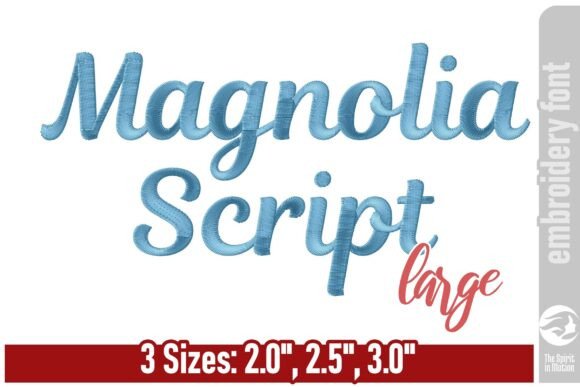
Magnolia Script Embroidery Font - Large
適切なデザイン要素を見つけるのは難しい場合がありますが、Magnolia Script Embroidery Font - Largeは作品を即座に引き立てる優れたコレクションを提供します。
POD(オンデマンド印刷)製品、結婚式の招待状、またはソーシャルメディアのグラフィックを作成している場合でも、Magnolia Script Embroidery Font - Largeは理想的です。